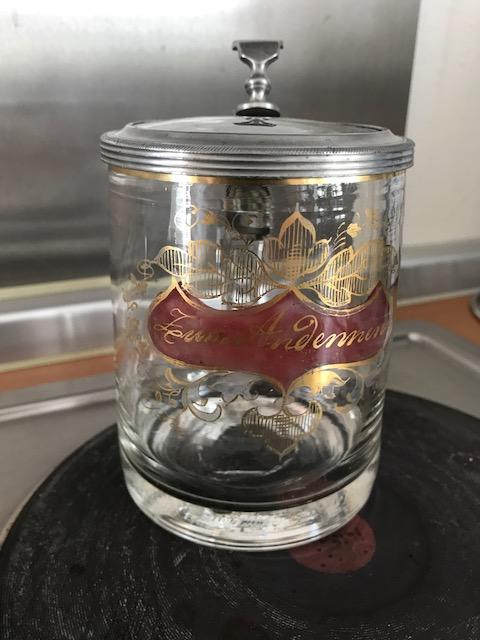
ich würde mich sehr über einen Hinweis freuen, der mir Aufschluss zum Alter dieses handgemalten Emblems gibt. Den Glaskrug selbst würde ich auf ca. 1850 oder früher eingrenzen.
War dieser Schrifttyp Mode zu dieser Zeit?
Die Bemalung/Beschriftung wird wohl aus der gleichen Zeit sein wie das Gefäß. Warum auch nicht? Die Schrift ist nichts Besonderes, eine lateinische Schreibschrift wie sie im 19. vielfach üblich war.
Ein Antiquitäten-Spezialist kann bestimmt weiterhelfen …